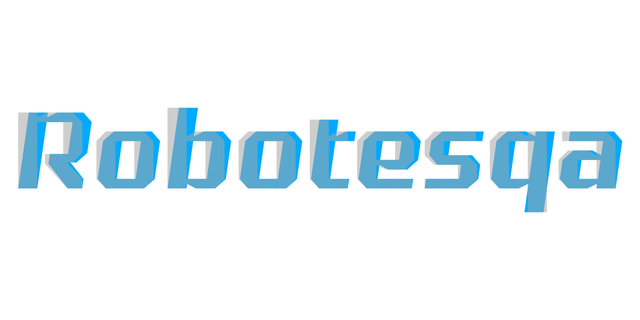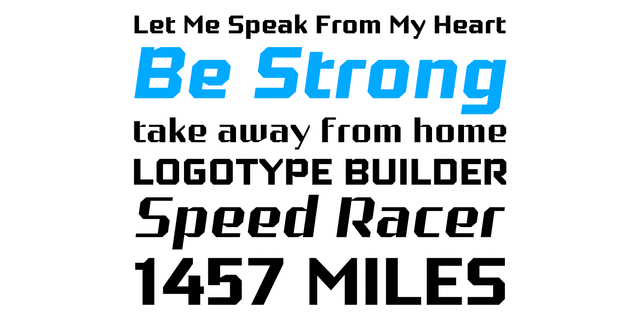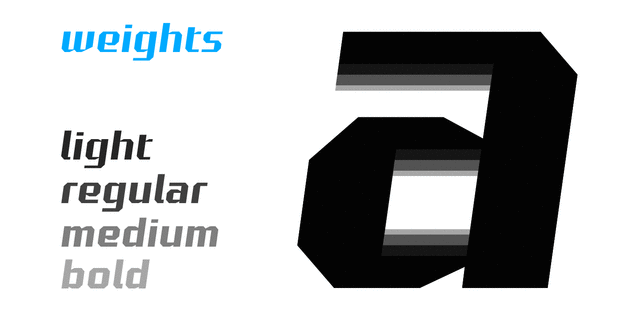
Идея создания шрифта Robotesqa 4F пришла в 2010 году в процессе дизайна интерфейса компьютерной игры (неопубликованной), а именно экранной статистики о прохождении уровней. Все символы латиницы и кириллицы создан в 2010 году, а остальные – в конце 2013 года, включая стрелки, иконки и прочее. Также были добавлены стилистические альтернативы, с более закрытой апертурой. Шрифт Robotesqa 4F выпущен Сергеем Ткаченко в 2013 году.
компьютерный, электронный, молодежный, ровный, квадратный, точный, логичный, холодный, автоматический, техногенный, твердый, статичный, резкий, четкий, устойчивый, стабильный, прямоугольный, городской, современный, машинный, инженерный, урбанистический, чертежный, надежный, уверенный, стальной, космический, убедительный, серьезный, сильный, индустриальный, железный, мужественный, военный, армейский, промышленный, спортивный, железнодорожный, футуристичный, ломаный, угловатый, заметный, броский, активный, рабочий, кинематографичный, граненый, игровой, смелый, быстрый, гоночный, скоростной, мотивирующий, суровый, громкий, крутой, амбициозный, мощный, внушительный, грубый, брутальный
LEGO Nexo Knights